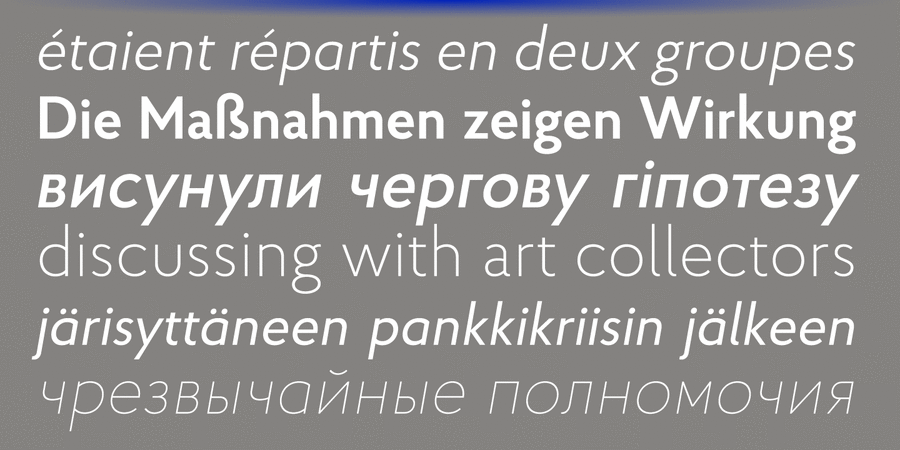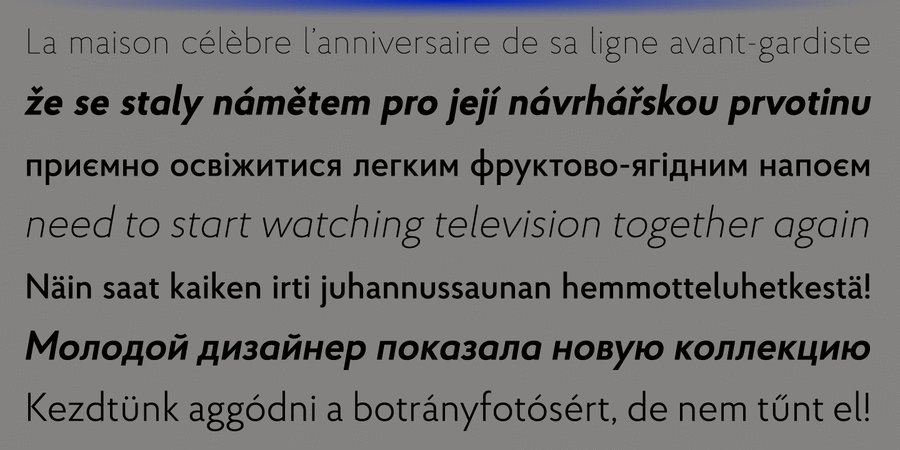
Опис гарнітури Proba Pro – геометричний гротеск зі зниженою висотою рядкових, помітними виносними елементами та легким гуманістичним відтінком. Гарнітура містить 7 варіантів насиченості + відповідні курсивні накреслення. Кожне накреслення підтримує численні мови, засновані на латиниці й кирилиці. Шрифт забезпечений багатьма OpenType фічами: лігатури, капітель, 4 набори цифр, 2 стилістичних набори, дроби, нижні та верхні індекси, адаптивну пунктуацію. Також є мовні альтернативи для румунської, каталонської і тюркських мов. Шрифт Proba Pro розробив і випустив Андрій Константинов у студії Mint Type в 2014 році.
Хіт 2010-х Proba Pro підтримує 84 мовиУкраїнська, Англійська, Німецька, Польська, Португальська, Іспанська, Французька, Російська, Чеська, Голландська, Італійська, Шведська, Турецька, Фінська, Білоруська, Сербська, Болгарська, Естонська, Литовська, Албанська, Африкаанс, Баскська, Бретонська, Валенсаска, Galician, Гельська (Шотландська), Данська, Індонезійська, Ірландська, Ісландська (Win), Каракалпацька, Каталонська, Норвезька, Окситанська, Ретороманська, Самі Лулі, Тсванська, Узбецька (Лат.), Фарерська, фризька, Чаморро, Естонська (Win), Південносаамська, Албанська (Win), Угорська, Верхньолужицька, Карельська, Латвійська (Mac), Литовська (Mac), Маорійські (Mac), Молдавська (Лат.), Нижньолужицька, Румунська (Win), Словацька, Словенська, Туркменська (Лат.), Хорватська (Win), Естонська (Mac), Курдська, Латишська, Маорійські, Руминська, Абазинська, Аварська, Агульська, Адигейська, Даргинську, Інгуську, Кабардино-Черкеська, Кабардинська, Карачаєво-Балкарська, Кумицька, Лакська, Лезгинська, Македонську, Мордовсько-Мокшанська, Мордовсько-Ерзянська, Ногайська, Рутульська, Табасаранська, Татська, Цахурська, Чеченська, Російська (XIX) Функції сімейства шрифтів Proba ProЗастосування гарнітури у верстці:
Асоціації з сімейством шрифтів Proba ProОсобистість і характер гарнітури:
делікатний, чистий, легкий, прохолодний, свіжий, модний, тонкий, сучасний, лаконічний, якісний, невагомий, прозорий, інтимний, крихкий, ніжний, повітряний, скляний, дротяний, худий, ясний, рівний, міський, формальний, зрозумілий, точний, Простий, комфортний, зручний, твердий, мотивуючий, сильний, переконливий